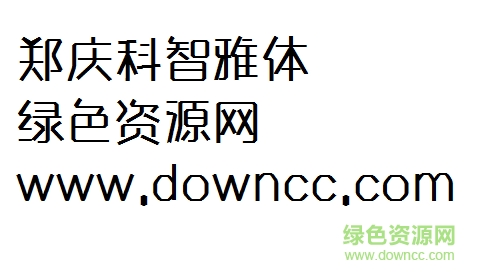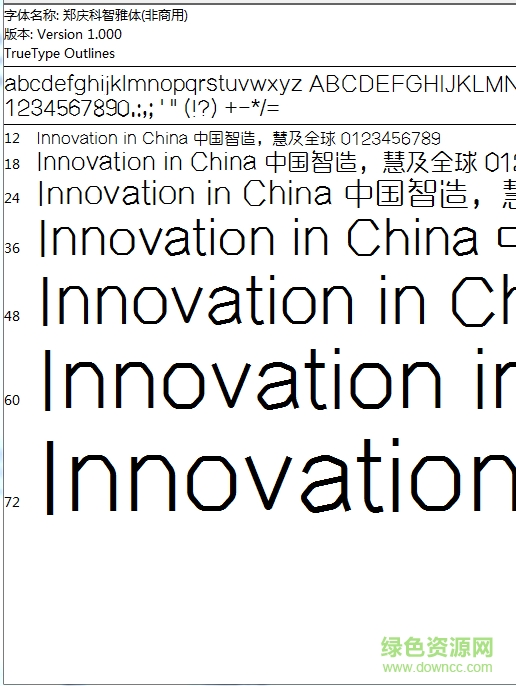
鄭慶科智雅體中
鄭慶科智雅體是一款非常有特點(diǎn)的中文字體軟件,智雅體十分清新文雅,字體筆畫粗細(xì)相間,整體非常好看,喜歡就到綠色資源網(wǎng)下載使用吧!
鄭慶科智雅體
可愛的智雅體,適用于名片設(shè)計(jì)、新聞媒體、宣傳海報(bào)、ppt、影視制作以及內(nèi)容用字等領(lǐng)域。